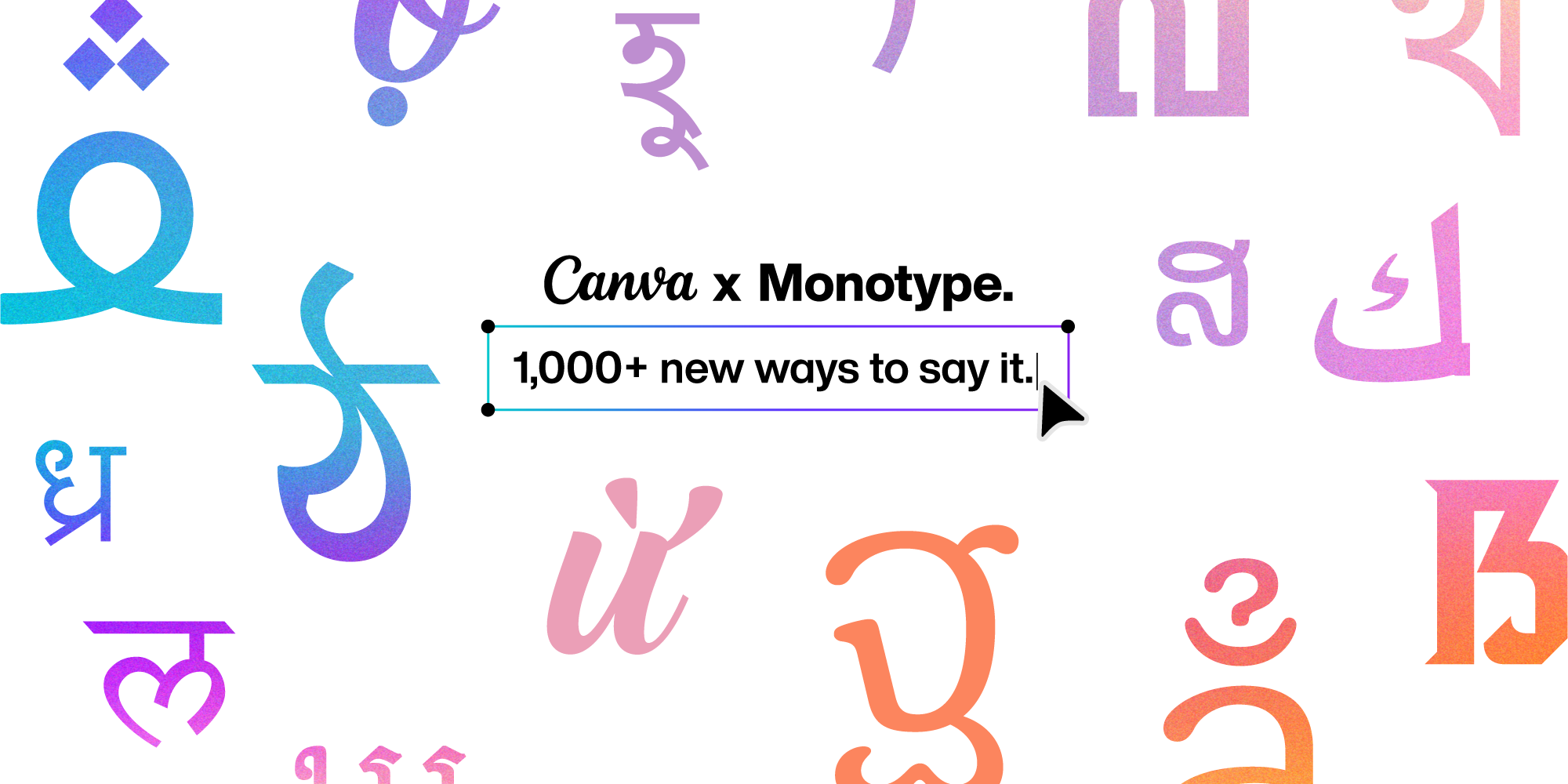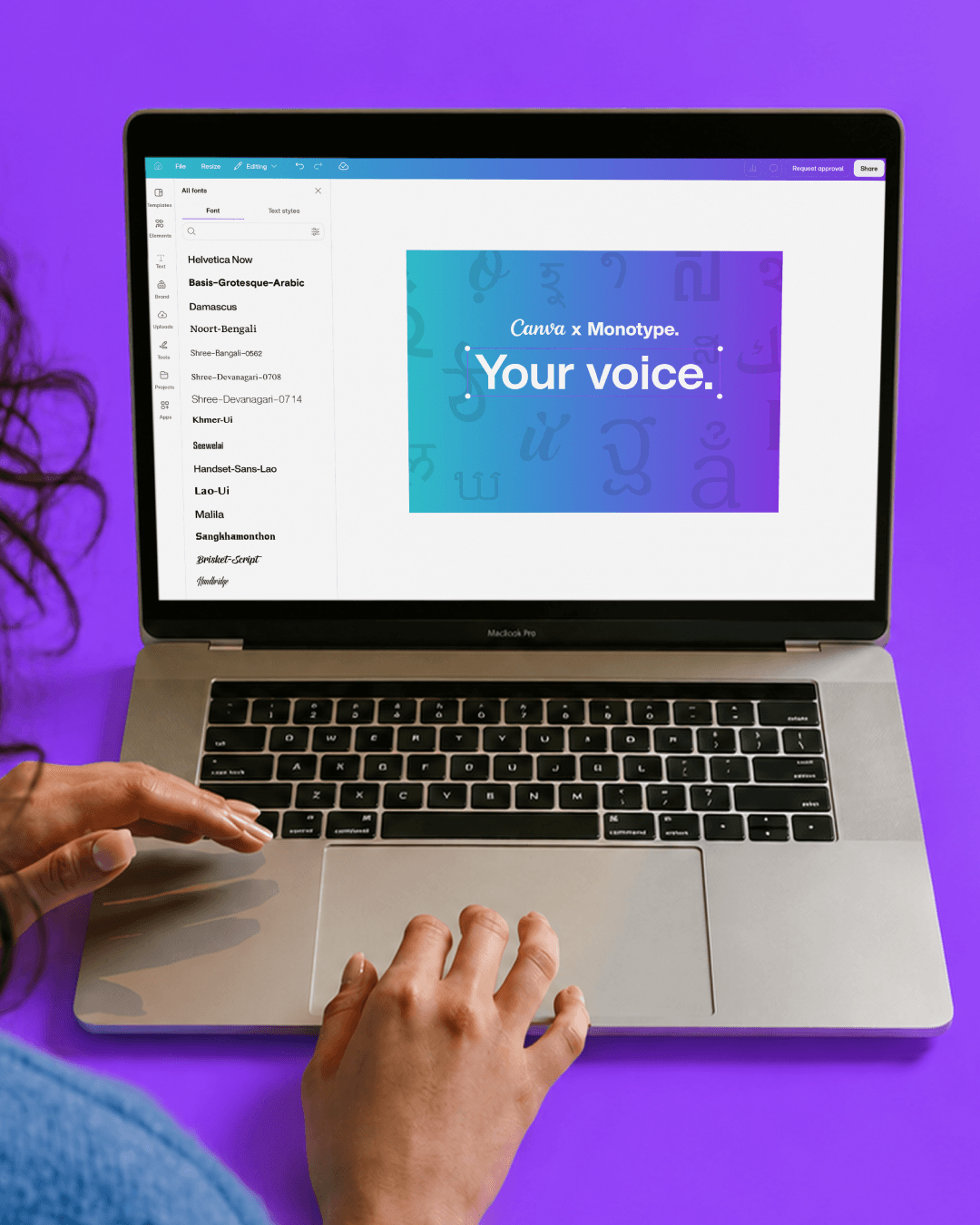
2026 年 9 月 24 日,Monotype 与全球视觉设计平台 Canva 今日宣布深化双方合作,为 Canva 全球创作者带来更丰富的字体选择,新增来自 Monotype 及其全球合作字体公司的 1,000 余款字体风格。此次扩充后,Canva 平台上提供的 Monotype 及其合作字体公司的字体风格总数已超过 3,000 款。
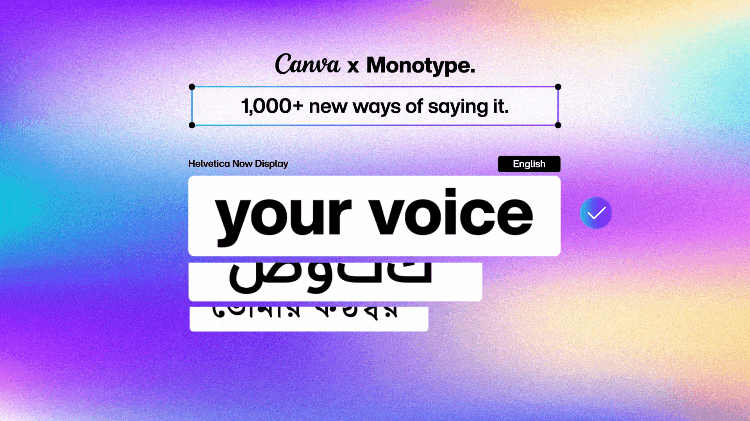
此次扩充大幅拓展了多个语言和书写系统的字体选择。这些语言此前在创作工具中一直缺乏足够的专业级字体支持,其中阿拉伯语、孟加拉语、印地语、高棉语、老挝语、泰语和越南语均有大幅新增。
2025 年,Canva 用户累计翻译了超过 1,700 万份设计,充分说明 Canva 用户正在跨语言、跨市场大规模地进行创作。随着这一趋势不断扩大,创作者需要的已不只是支持某种语言的字体;他们还需要在这些语言内部拥有足够丰富的字体多样性,才能创作出具有独特风格、真正贴合自我表达的作品。
Canva 与 Monotype 共同规划了这次扩充的字体库,字体的选择来自 Monotype 自有字库以及其合作的全球字体公司与设计师。新字库涵盖衬线体、无衬线体、展示体、手写体和正文体等多种风格,让创作者在沟通与自我表达时拥有更多选择。
字体选择增幅最大的语言包括印地语、孟加拉语和越南语:本次扩充新增 99 个印地语字体家族、共 298 款风格;72 个孟加拉语字体家族、共 237 款风格;以及 114 个支持越南语的字体家族、共 249 款风格。此外,阿拉伯语、高棉语、老挝语和泰语的字体选项也得到进一步扩充。
其中的字体包括:Colophon Foundry 出品的 Basis Grotesque™ Arabic(阿拉伯语)、TypeTogether 出品的 Noort Bengali(孟加拉语)、Modular InfoTech 出品的 Shree Devanagari(印地语)、Anagata Type 出品的 Seewelai(高棉语)、Monotype 出品的 Handset™ Sans Lao(老挝语)、Cadson Demak 出品的 Malila(泰语),以及 Måns Grebäck 出品、支持越南语的 Brisket Script。
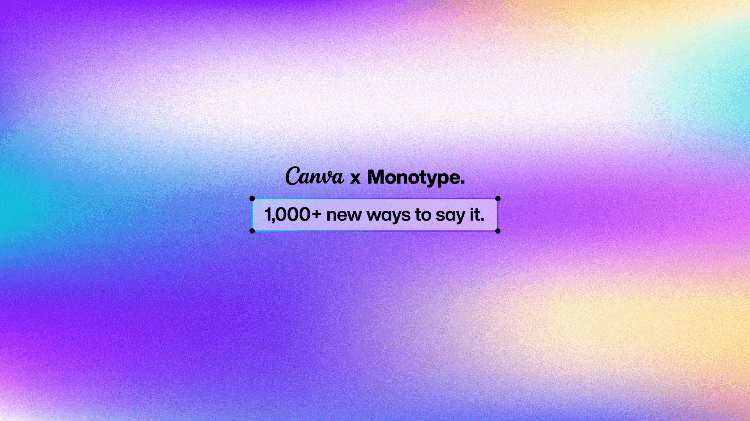
此次合作基于 Canva 与 Monotype 于 2023 年达成的伙伴关系。自那以后,Monotype 及其合作字体公司的字体已被用于超过 10 亿份 Canva 设计作品,足见字体选择对 Canva 全球创作者社群的重要意义。
“创意人士正在面向更多市场使用更多语言创作内容。在这样的环境下,做出独特性尤为重要。字体是让一个想法、一种身份或一个品牌被一眼认出的关键。我们与 Canva 深化合作,就是为了给创作者更多选择,让他们的作品既能脱颖而出,又能以贴近受众的方式沟通”Monotype 首席营销官 Karen Brewer 表示。
“仅仅支持一门语言的字符只是起点,”Monotype 全球创意策略负责人 Charles Nix 表示,“真正的选择意味着拥有不同的声音、风格和个性可供挑选。我们为 Canva 带来 1,000 余款、覆盖多种书写系统的新字体风格,就是要让更多创作者自由地找到不仅贴合其语言、也贴合其视觉表达方式的字体。”
“Canva 用户面向全球各地的受众、文化和市场进行创作。随着用户不断壮大,我们希望他们可用的创作选择也一同成长。深化与 Monotype 的合作,让更多语言的创作者得以接触到更广泛的字体资源,拥有更多方式表达他们想要传达的内容,”Canva 全球内容合作负责人 Morgan Selzer 表示。
数据一览:
来自 Monotype 及其全球合作字体公司网络的 1,000 余款新增字体风格现已在 Canva 上线,使字体总数超过 3,000 款。
此次扩充丰富了阿拉伯语、孟加拉语、印地语、高棉语、老挝语、泰语和越南语的字体选择。
新增 99 个支持印地语的字体家族,共 298 款风格;
新增 72 个支持孟加拉语的字体家族,共 237 款风格;
新增 114 个支持越南语的字体家族,共 249 款风格。
Monotype 及其合作字体公司的字体风格已被用于超过 10 亿份 Canva 设计作品。